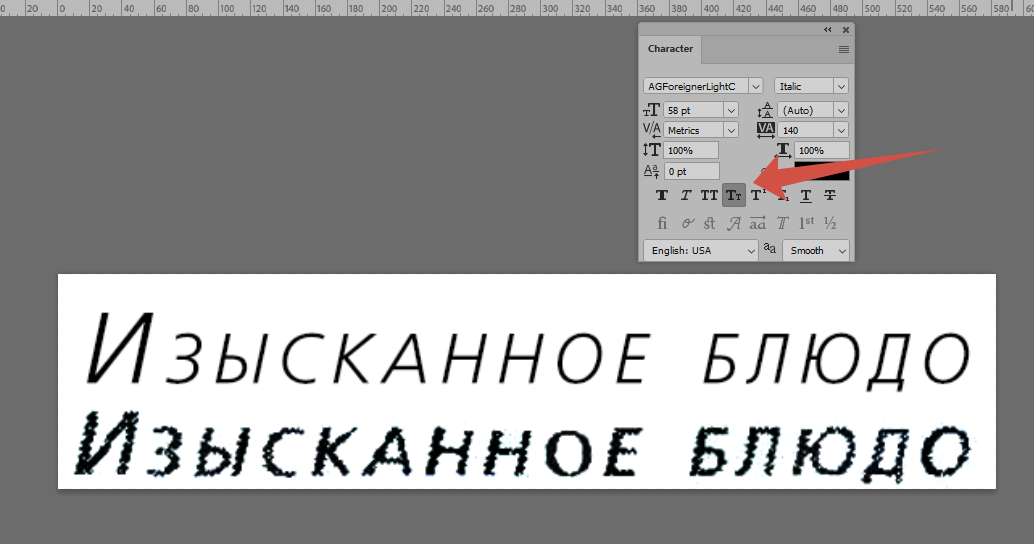
Странный шрифт
Сосед притащил отсканированную поваренную книжку отвратительного качества и попросил улучшить для чтения. Что-то удалось поправить, но есть проблема с одним странным шрифтом - строчные буквы очень похожи на прописные, да еще курсив. Есть предположения?
Еще текст покажите
Капитель бывает в шрифте или программная, с таким качеством непонятно.
Думаю, стоит добавить для топикстартера, что это скриншот из индизайна.
Думаю, стоит добавить, что использование программных капителей может привести к неприятному удивлению результатом печати )))
По существу:
улучшить для чтения.
1) Распозавать и верстать заново. Как уже обозначили выше.
2) Может стоит поискать оригинал с которого сканировали и приобрести?
Это капители — начертание строчных букв как заглавных.
Только есть пару вопросов:
- для правки скана использовал порталки acrobat и photoshop из интернет, там есть капители?
- acrobat показал на таком тексте странный шрифт - Calibri-Italic-8127. Предполагаю, что это наиболее близкий. Но попытка поправить текст получается через раз. Возможно, где-то ошибаюсь...
• Акробат не предназначен для правки текста в таких объемах как у Вас. Кроме того, Ваша цель — улучшить читаемость, что не обязывает сделать шрифт один-в-один.
- Объем текста небольшой, всего 50 страниц. Поэтому и согласился помочь (взаимовыручка). Просто у соседа жена калинар-любитель (шучу), а она достала мужа - что там написано.
из области вёрстки открыл фотошоп
скопировал картинку из топика, куда?
Логично, что в ФШ, или определить шрифт (ах да, я же еще сначала в ФЭ подобрал наиболее похожее)
нужно сразу в ИД?
1. У меня нет необходимости что-то верстать, тем более печатать. Только оказание посильной помощи.